さて、今回はwebフォントサービスの「Googleフォント」について実際のデザイン業務で使用しやすい・よく使用するフォントをご紹介していきたいと思います。
webフォントとは?
フォントは通常、ローカル環境(自分のPC)にあるフォントを使用する仕組みとなっており、ユーザーによって見えるフォントが変わってしまうのですが、webフォントはフォントデータをサーバーから読み込み、ページに表示させることができるのでどの端末でも同じフォントが表示されるようになります。
・デザイン性が上がる
・どの端末でも同じフォントで表示される
といったメリットがある一方で、
・たくさんのwebフォントを使用しすぎると表示速度が遅くなる
・日本語に対応しているwebフォントが少ない
といったデメリットもあります。
Googleフォントとは?
Goolgeが無料で提供しているwebフォントのサービスで800種類以上のフォントを使用することができます。
商用利用もできるので幅広く使用することができます。
おすすめのGoogleフォント
Lato
バランスや字詰め具合など、上品で柔らかい雰囲気のフォントです。
どのデザインテイストでも合わせやすいので私もよく使用します。
Roboto
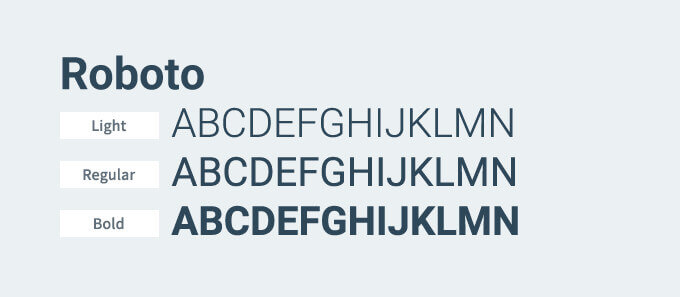
太さがたくさん用意してあるので、幅広く使用できるフォントです。
可読性もよく、文字を読ませたい・しっかりした印象を与えたいといったときにおすすめです。
Montserrat
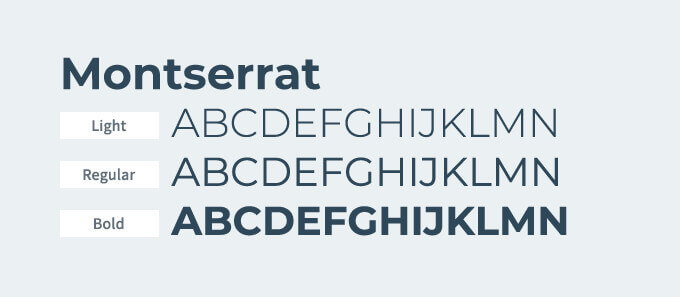
少し縦に潰したような形で、タイトルや日付部分に使用しやすいフォントです。
ゴシック体ですが少し丸みもあり、可愛らしい印象を与えます。
Oswald
かっこいい縦長のフォントで、スポーティーな力強い印象を与えます。
細いウェイトを使用すればスタイリッシュな印象にもなります。
Josefin San
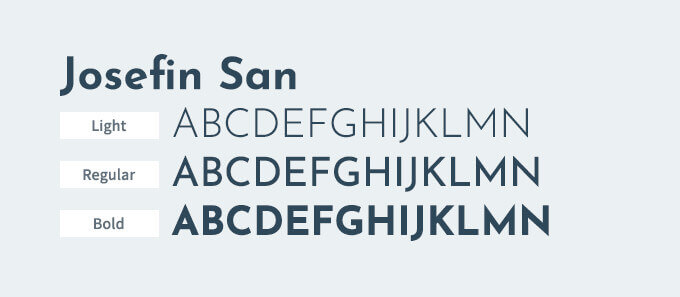
特に細いウェイトはシックで女性らしい印象を与えます。
デザイン性があるフォントでジーニアスウェブのオフィシャルサイトでも使用されています。
Quicksand
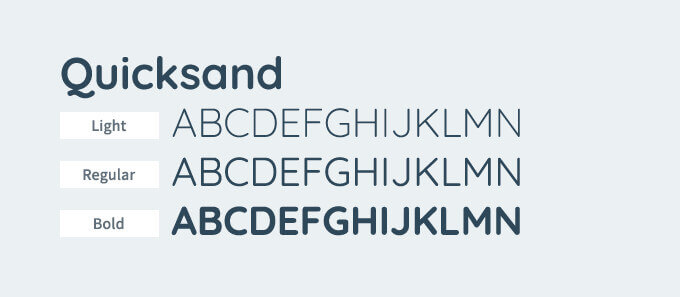
丸っこく親しみやすい印象を与えるフォントです。
女性向けのサイトデザインやミニマルデザインにマッチします。
Slabo
読みやすく、長文にも使用しやすいフォントです。
Rajdhani
全体的に丸みがありながらも、カクカクしているのでデジタル系、サイバー系のデザインに使用しやすいフォントです。
ローカルにあるフォントだけではただ打っただけの文字に見えますが、デザイン性のあるwebフォントを使用することでデザインにアクセントもつき幅広いデザインを作成することができます。